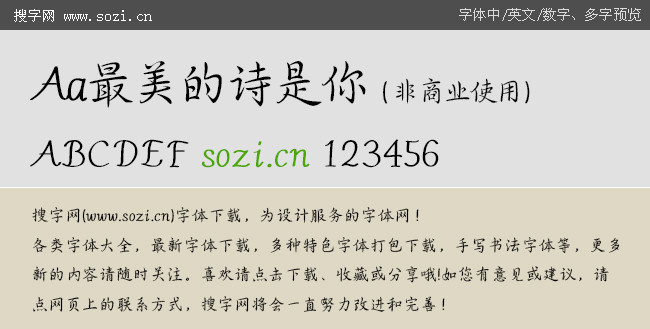
Aa最美的詩是你(非商業(yè)使用)
搜字網(wǎng)給大家提供一款A(yù)a最美的詩是你(非商業(yè)使用)中文字體下載,該字體是一款手寫中文字體,這款字體端莊,書寫簡潔大方,適合包裝設(shè)計、書裝設(shè)計、海報設(shè)計等應(yīng)用(此字體為個人非商用版,商用可以聯(lián)系QQ:1006760504)。